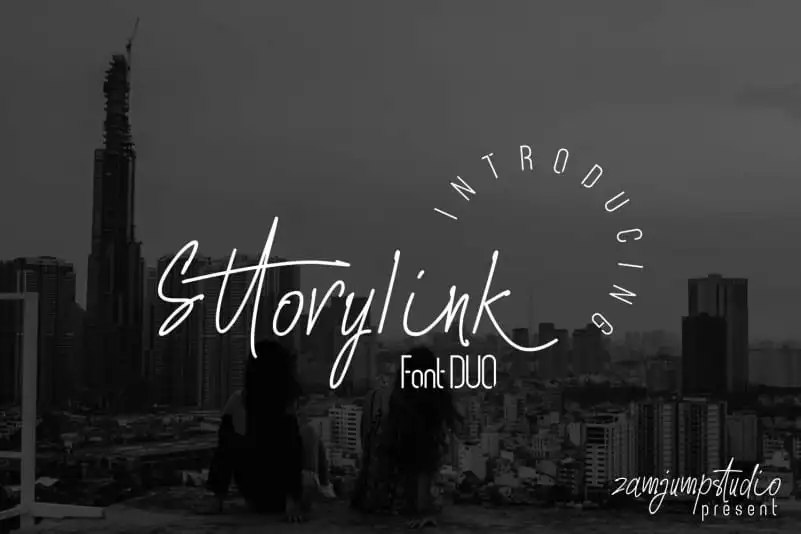
A font Sttoryink Font Duo é uma combinação elegante e moderna perfeita para estilos de negócios sofisticados e fashionistas. Inspirada na experiência do Instagram Stories, essa script-font tem um estilo devido à simulação cuidadosa com esferográficos, combinando tanto elementos femininos quanto elegantes e contemporâneos. É livre e fluido, perfeitamente adaptado para marcas de moda, lojas online de e-commerce ou negócios que desejam adquirir uma aparência sofisticada e chique. A Sttoryink é uma escolha irresistível para qualquer pessoa procurando expressar sua marca com um visual moderno e atemporal.